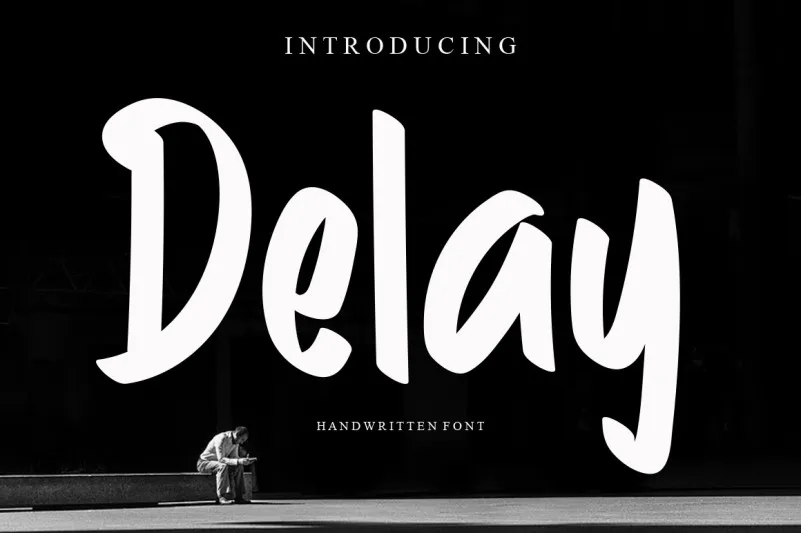
Aqui está a descrição conforme solicitado: Esta é uma fonte escrita a mão única, divertida e amigável. Espanhola para Instagram ou script manual para projetos DIY? Este é o seu lugar. Com um toque de criatividade, esta fonte transformará qualquer projeto em arte genuína. A fonte ‘Delay Font’ é perfeita tanto para quem procura uma alegria rápida no Instagram quanto para aqueles que querem dar vida à calligrafia manuscrita num DIY. Seja você um fã de texturas e formas diferentes, ou simplesmente alguém que adora criar algo original em seu próximo projeto gráfico, ‘Delay Font’ é a escolha perfeita. Com uma paleta de opções únicas e uma personalidade encantadora, esta fonte traz aos seus projetos um toque único e divertido. Seja para anúncios, designs de aplicativos ou qualquer outro projeto em que você use texto, ‘Delay Font’ irá tornar seu trabalho impecável. Descubra o potencial incrível desta fonte neste blog de recursos gráficos. Vamos explorar juntos como ela pode enriquecer os seus projetos e criar um toque especial neles.